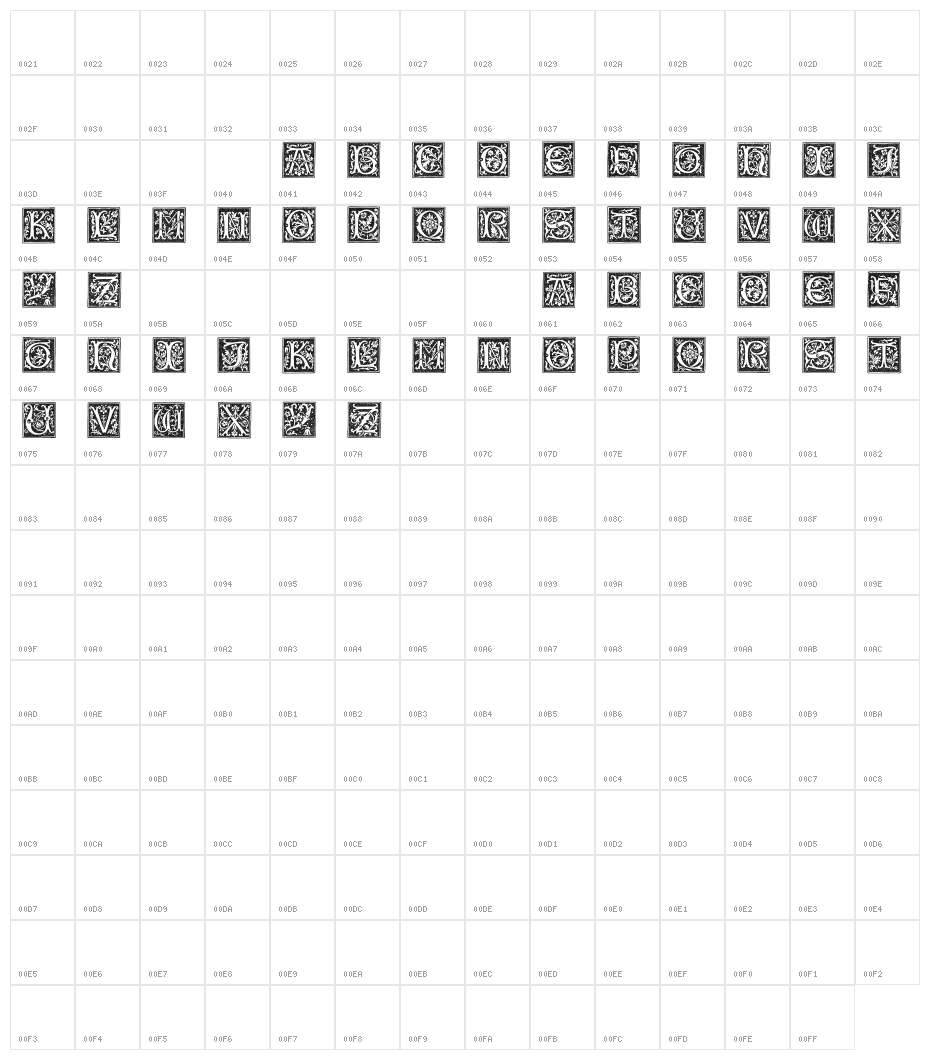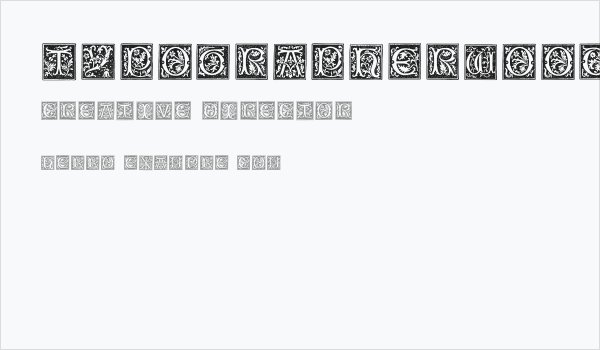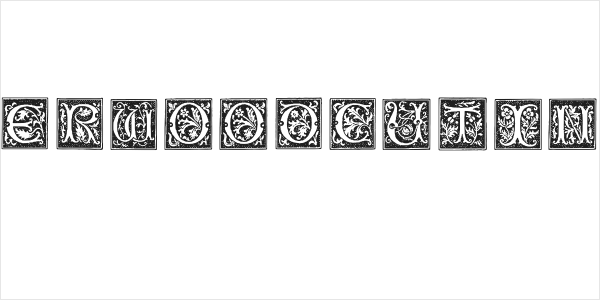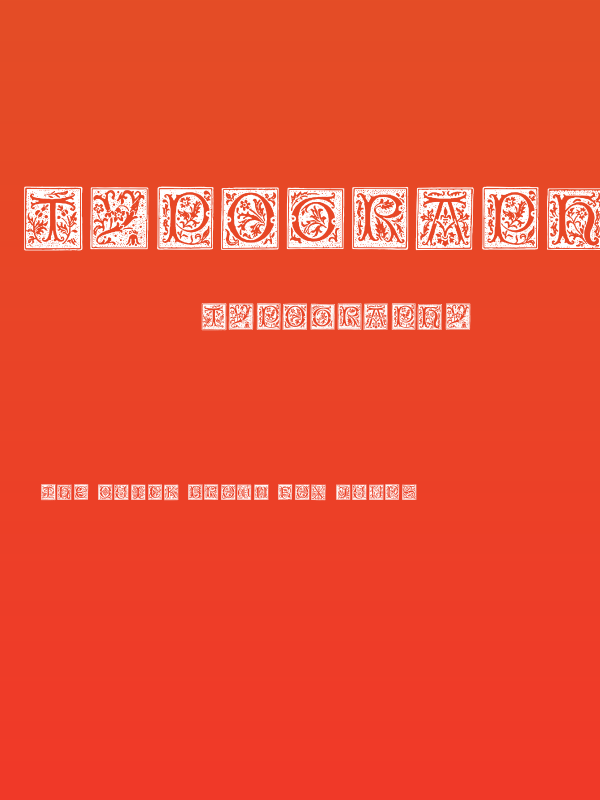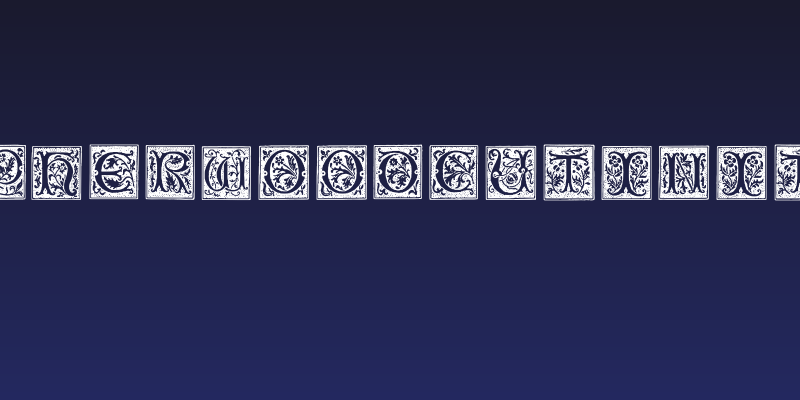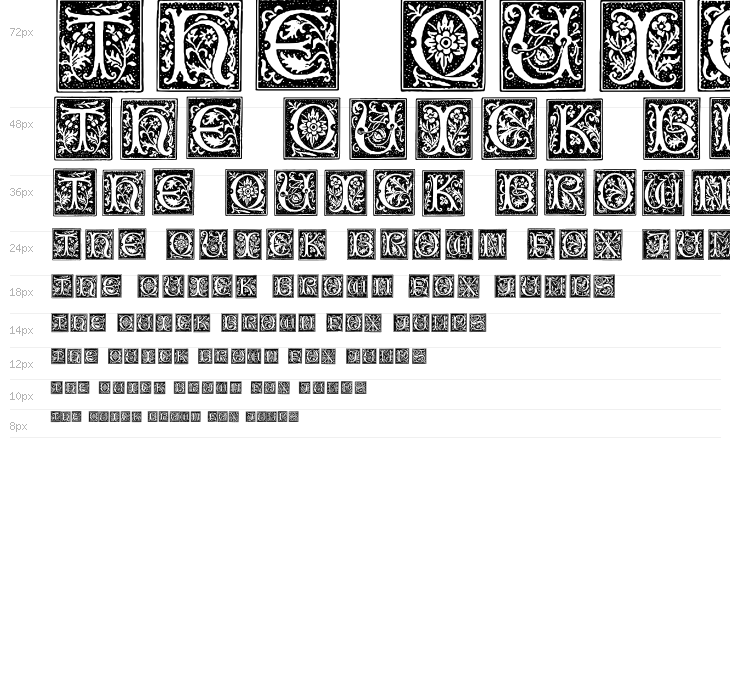
TypographerWoodcutInitialsOne Font
| Progetti proposti | Ideal for vintage-themed invitations, historical posters, book covers, and artistic projects requiring a classical touch. |